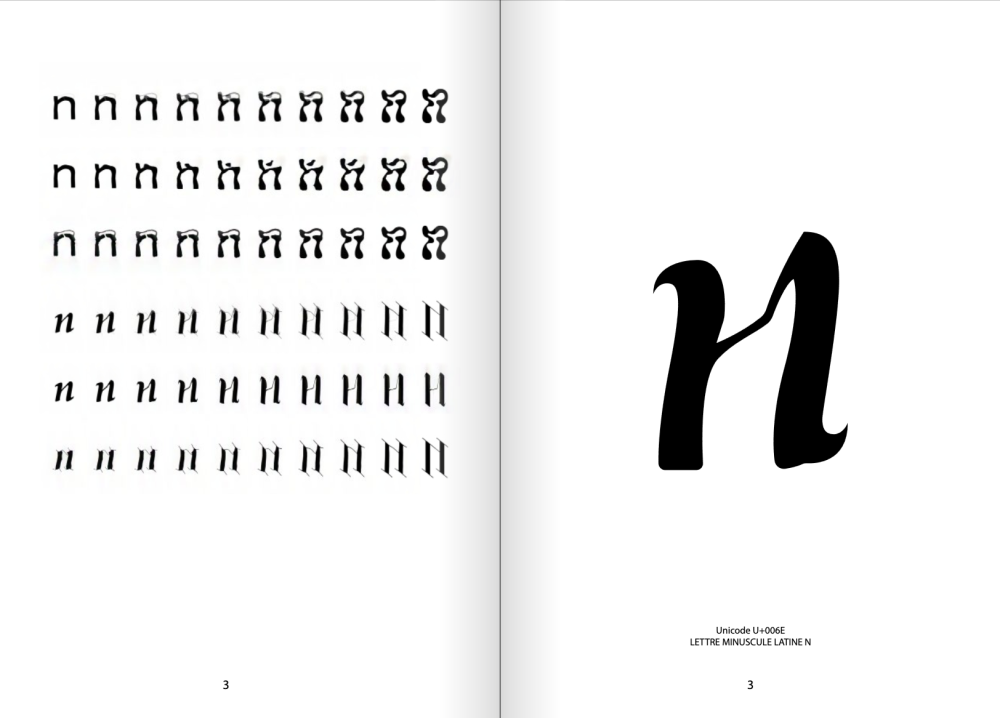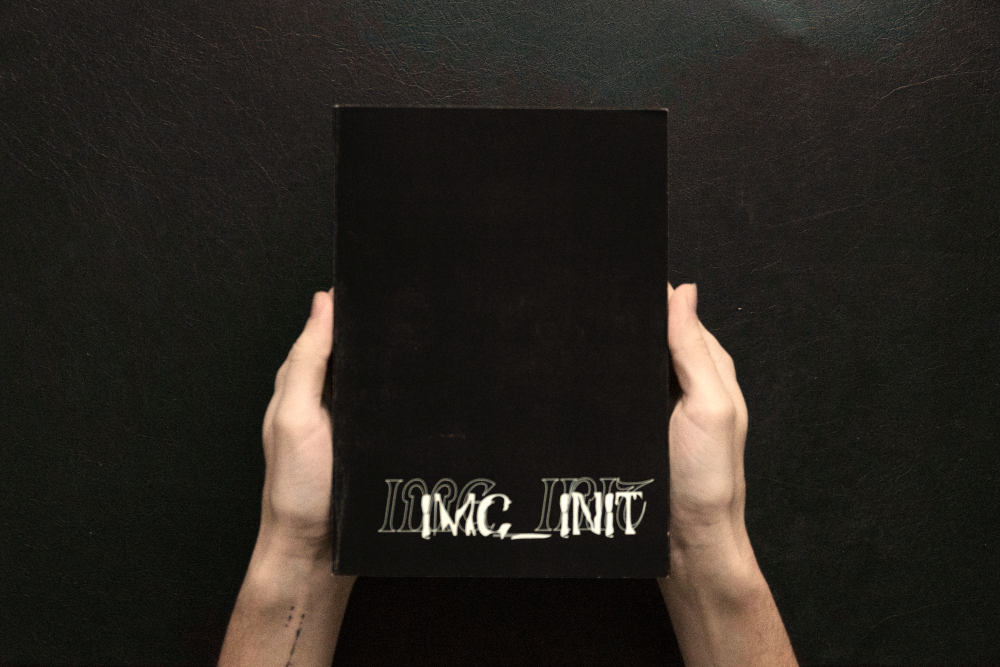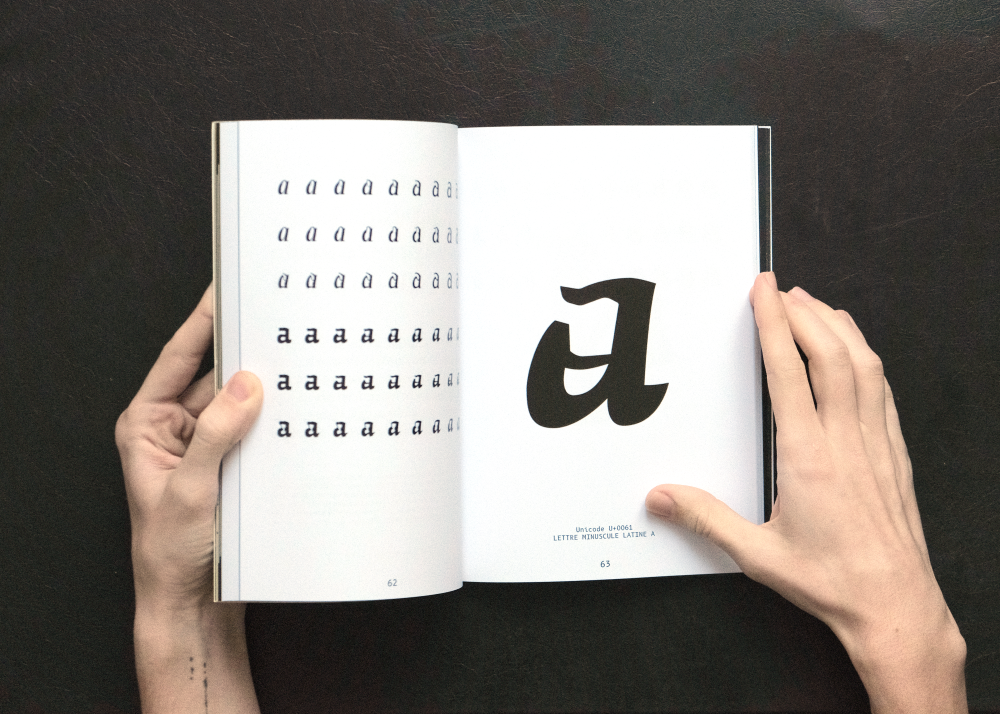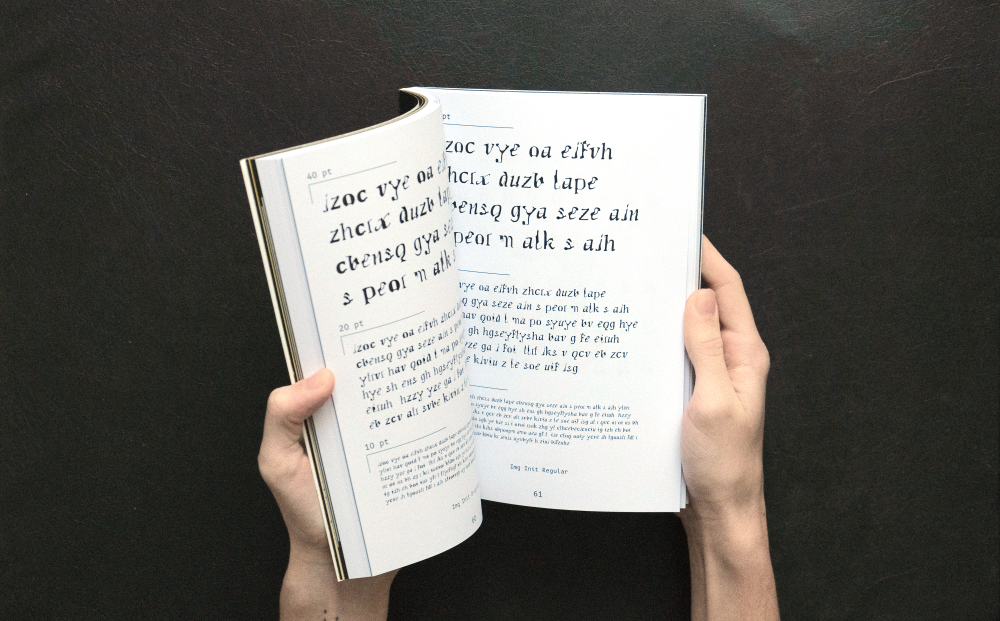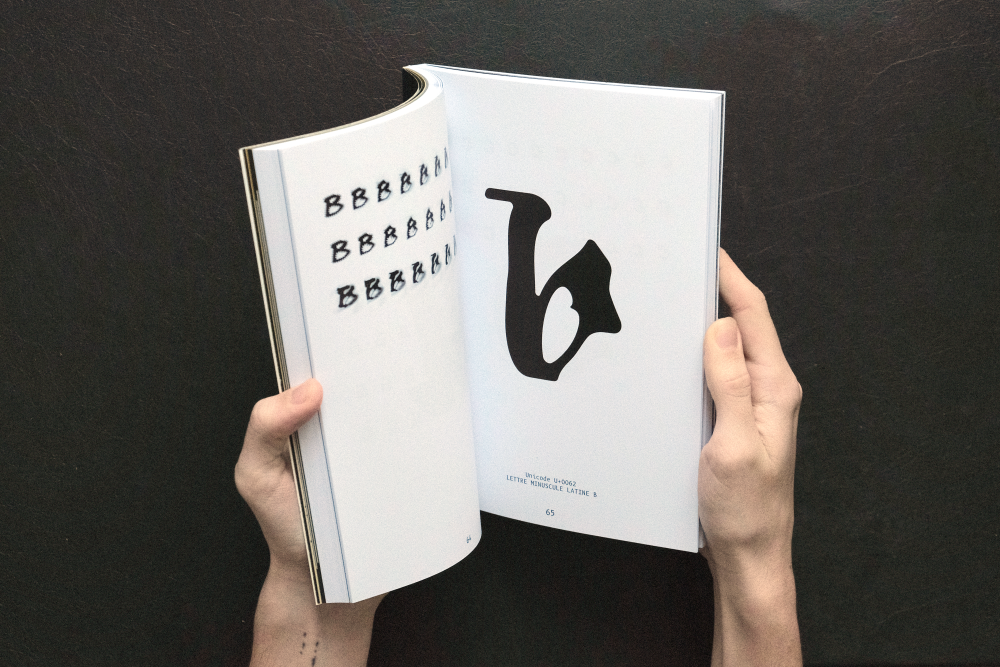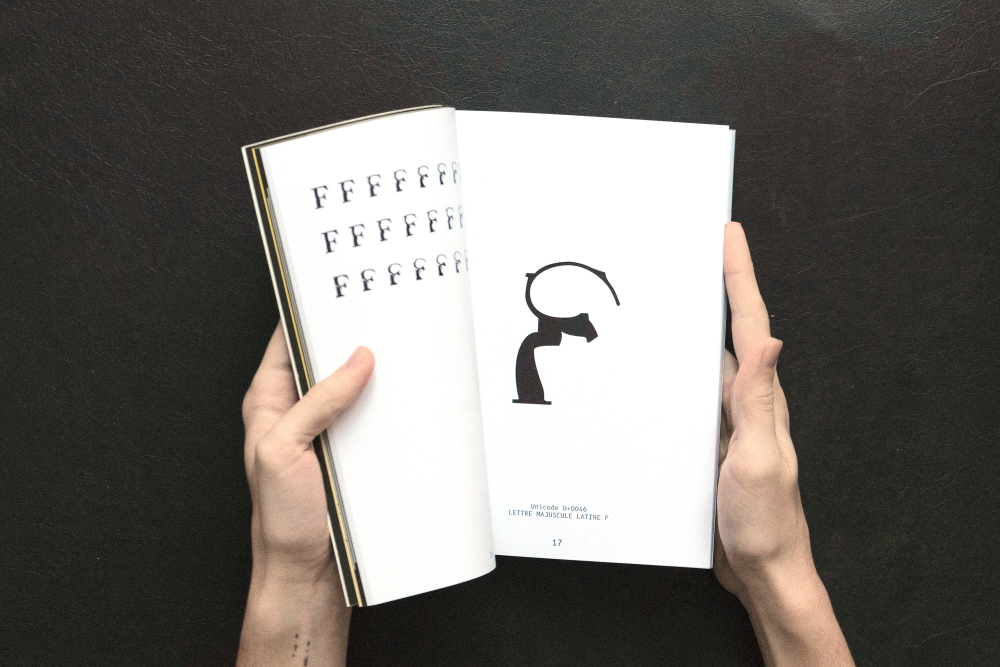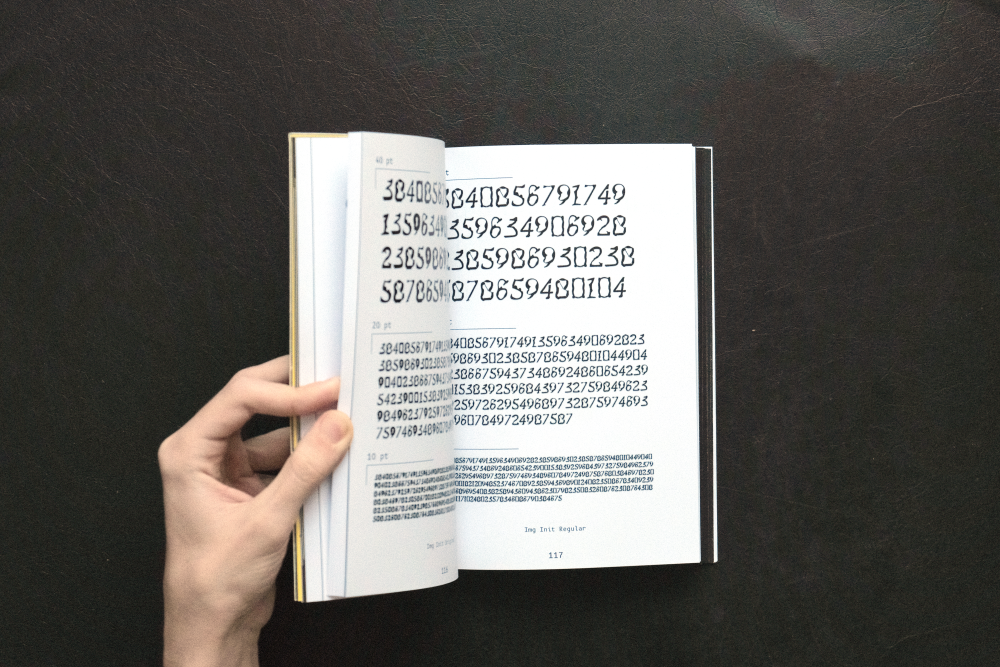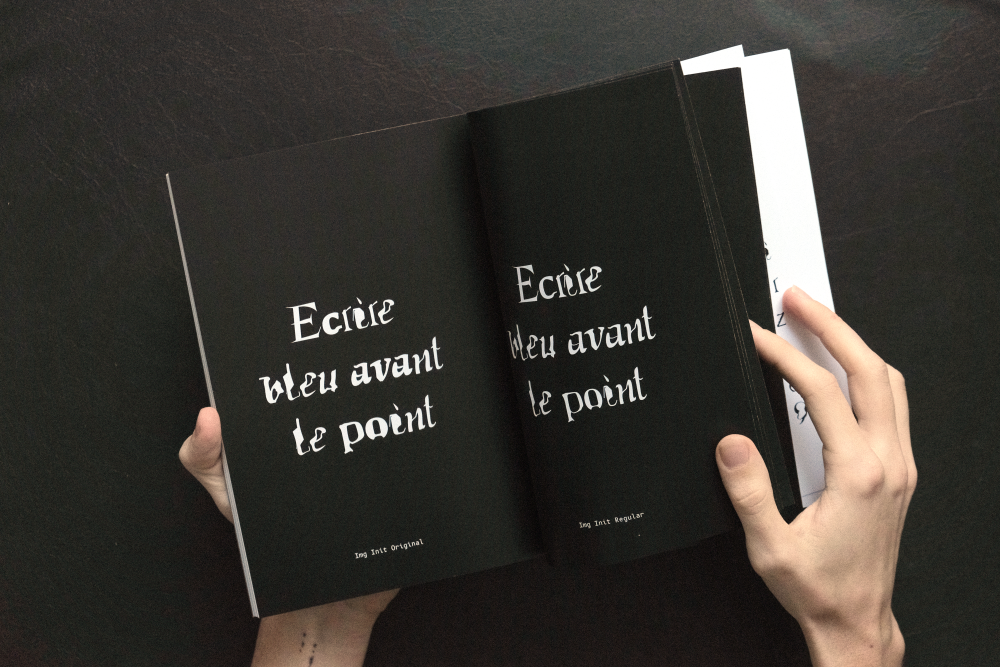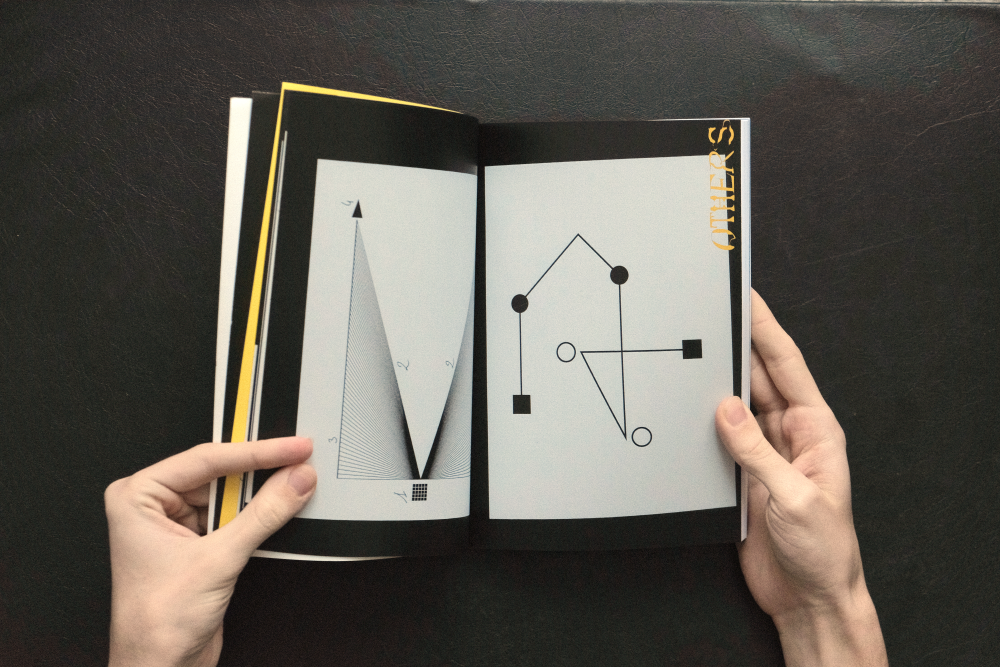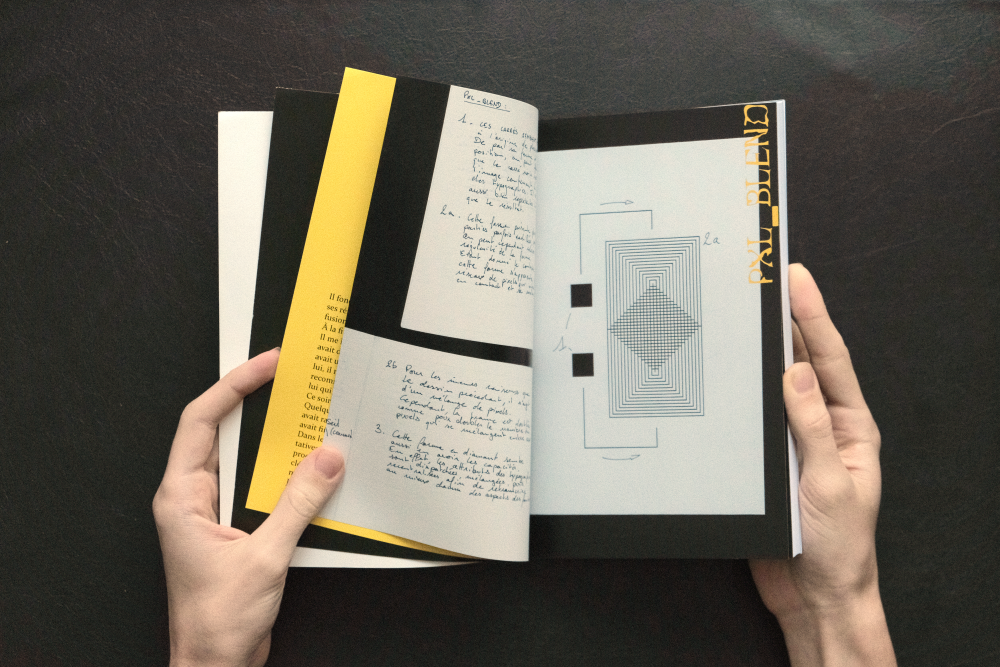
Voici la Imginit! c'est une typo qui a été créée durant mon dnmade design graphique à Duperré à l'occasion de mon projet de diplôme. Il manque plein de caractères et c'est peut être compliqué de reproduire exactement les même étapes de production puisque c'était avec une IA que j'avais créé, mais vous voyez l'idée générale. Il manque surtout toute la ponctuation et les accents. J'arrive pas a me décider sur faire des nouvelles lettres, par exemple pour le "é" si je reprends le "e" de base avec un accent ou si on change de lettre entièrement.
C'est quoi le processus concrètement ? C'est quoi les étapes de ton IA ? Partant aussi pour compléter la typo j'enverrai les retours dans un autre post.
Imginit (le nom de mon IA à la base) partait d'une base de données de + de 300 typographies. À chaque fois qu'elle dois réécrire un nouveau caractère, elle cherche parmi toutes ces typo et écrit la lettre dans des centaines de manières différentes. Ensuite il les mélange visuellement entre elles et créé des amalgames de lettres qui sont ensuite remélangées etc etc. Certaines itérations sont retirées en cours de route si elles sont trop éloignées d'un résultat cherché, ou mises de côté pour recommencer un cycle de mélanges. À la fin c'est au graphiste d'extraire ces images de l'ordinateur pour redessiner les lettres dans un format lisible par l'utilisateur.
Je me permet d'ajouter quelques caractères supplémentaires à la font si vous voulez les retoucher !
Typo tout à fait adaptée au générique de Nosfératu !!! j'adore ;-)
Cette font a été produite dans un contexte de recherche sur l'Intelligence Artificielle en 2020, elle est la résultante d'une collaboration entre un cerveau numérique et un étudiant en design graphique. Les formes sont dans un premier temps produites par l'IA qui communique les informations selon sa vision de la lettre, puis le graphiste vient traduire ces formes en lettres.
Imginit